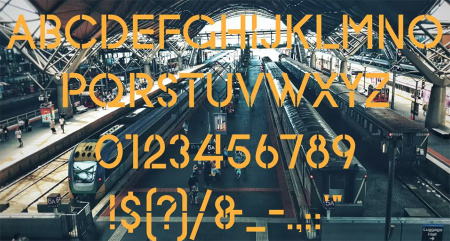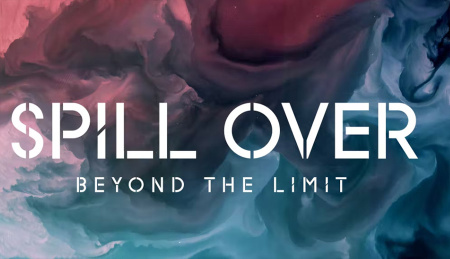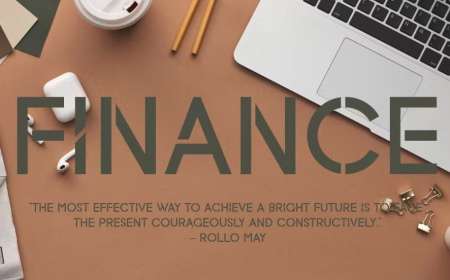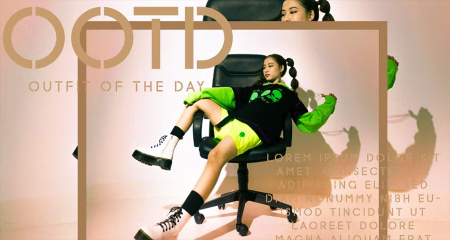
فونت انگلیسی رایگان Himalaya از جی اف ایکس دانلود. یک فونت ساده و مدرن برای اهداف چند منظوره می باشد. بسیار مناسب برای شما که به یک تایپ فیس برای طراحی لوگو، مجله، رسانه های اجتماعی، بروشور و بسیاری موارد دیگر نیاز دارید. برای مشاهده تصاویر این فونت رایگان انگلیسی مدرن به ادامه مطلب مراجعه کنید.
✅ نام فونت انگلیسی: Himalaya
✅ حروف بزرگ
✅ حروف کوچک
✅ اعداد
✅ نقطه گذاری